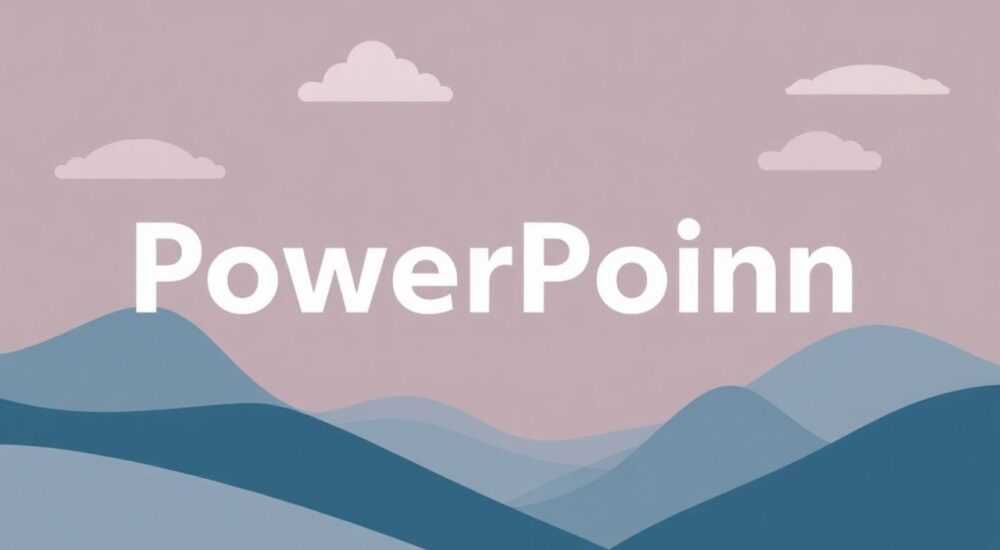
Как установить шрифт для презентации powerpoint
Установка шрифта для презентации в PowerPoint — это важный этап создания визуально целостного и профессионального выступления. Несмотря на кажущуюся простоту, процесс может вызывать трудности, особенно если шрифт не отображается на другом устройстве или требует установки из внешнего источника. Чтобы презентация корректно открылась у всех зрителей, нужно не только выбрать подходящий шрифт, но и правильно его интегрировать в файл.
Создание презентации — это не просто подбор текста и изображений, а продуманная типографика, где каждый элемент влияет на восприятие информации. Шрифт задаёт тон: деловой, креативный, строгий или дружелюбный. Однако даже самый идеальный выбор может «сломаться», если получатель не имеет установленного шрифта. В результате текст может отобразиться стандартным шрифтом, что испортит весь дизайн. Поэтому важно не только выбрать стиль начертания, но и обеспечить его стабильную работу на любом устройстве. В этой статье мы детально разберём, как установить шрифт для презентации PowerPoint, какие форматы поддерживаются, как встроить шрифты в файл и избежать распространённых ошибок.
Установка шрифта в систему
Прежде чем использовать шрифт в PowerPoint, его нужно установить в операционную систему. Без этого шага шрифт не появится в списке доступных в программе. Обычно шрифты распространяются в виде файлов с расширениями .ttf (TrueType Font) или .otf (OpenType Font). Эти форматы поддерживаются как Windows, так и macOS, но способы установки немного различаются.
На Windows 10 и 11 установка шрифта занимает всего несколько кликов. Скачанный файл шрифта можно открыть двойным щелчком, после чего откроется предварительный просмотр. В верхнем правом углу окна будет кнопка «Установить». Нажав её, вы добавите шрифт в систему. Альтернативный способ — перетащить файл шрифта в папку «Шрифты» (C:WindowsFonts), которая доступна через Проводник или Панель управления.
На macOS процесс аналогичен: достаточно открыть файл шрифта с помощью приложения «Просмотр шрифтов», затем нажать «Установить шрифт». Система автоматически добавит его в библиотеку. После установки перезапускать PowerPoint не требуется — новый шрифт появится в списке сразу после обновления программы.
Если вы работаете в команде или готовите презентацию для коллег, обязательно уточните, установлен ли нужный шрифт на их устройствах. В противном случае они увидят замену шрифта на системный, что может повлиять на макет. Особенно это критично для кастомных или дизайнерских шрифтов, которые не входят в стандартный набор Microsoft Office.
Пошаговая инструкция для Windows
- Скачайте файл шрифта (.ttf или .otf) с доверенного сайта, например Google Fonts, DaFont или FontSpace.
- Найдите скачанный файл в папке «Загрузки» и дважды щёлкните по нему.
- В открывшемся окне предварительного просмотра нажмите кнопку «Установить».
- Дождитесь завершения установки и откройте PowerPoint.
- Проверьте наличие шрифта в меню «Шрифт» на вкладке «Главная».
Добавление шрифта в PowerPoint
После установки шрифта в систему он автоматически становится доступным в PowerPoint. Откройте программу, создайте новую презентацию или откройте существующую. Выделите текстовое поле, которое нужно изменить, и перейдите на вкладку «Главная». В группе «Шрифт» найдите выпадающий список со всеми доступными шрифтами. Пролистайте вниз — там должен появиться ваш недавно установленный шрифт.
Если шрифт не отображается, попробуйте перезапустить PowerPoint. Иногда программа не обновляет список шрифтов без перезагрузки. Также убедитесь, что вы установили именно тот файл, который открывается — некоторые шрифтовые пакеты содержат несколько файлов (например, Regular, Bold, Italic), и каждый из них нужно устанавливать отдельно.
PowerPoint позволяет быстро применять шрифт ко всему слайду или всей презентации через функцию «Замена шрифта». Для этого:
- Перейдите на вкладку «Главная» → «Редактирование» → «Заменить» → «Заменить шрифты».
- В открывшемся окне выберите шрифт, который хотите заменить (например, Calibri).
- Во втором поле выберите новый шрифт из списка.
- Нажмите «Заменить» — все вхождения старого шрифта будут изменены.
Это удобно при массовом обновлении оформления, особенно если презентация уже содержит много текста. Однако будьте осторожны: замена применяется ко всем слайдам, включая заголовки и подзаголовки, если они используют выбранный шрифт.
Как использовать шрифт в мастере слайдов
Чтобы шрифт стал частью фирменного стиля презентации, его можно задать в мастере слайдов. Это гарантирует единообразие на всех слайдах.
- Перейдите на вкладку «Вид» → «Образец» → «Образец слайдов».
- Выберите главный образец (верхний слайд в левой панели).
- Выделите текстовые поля для заголовков и основного текста.
- Измените шрифт на нужный, задайте размер, цвет и интерлиньяж.
- Закройте режим образца — изменения применятся ко всем слайдам, основанным на этом макете.
Теперь любой новый слайд будет автоматически использовать установленный шрифт. Это особенно полезно при создании корпоративных презентаций, где важна единая визуальная идентичность.
Встраивание шрифтов в файл презентации
Один из самых важных шагов — встраивание шрифтов в файл. Даже если вы установили шрифт на своём компьютере, при открытии презентации на другом устройстве он может не отобразиться. PowerPoint по умолчанию не встраивает шрифты, чтобы уменьшить размер файла. Но эту настройку можно изменить.
Чтобы встроить шрифты:
- Откройте презентацию в PowerPoint.
- Перейдите в «Файл» → «Параметры» → «Сохранение».
- Найдите раздел «Встраивание шрифтов в файл».
- Поставьте галочку «Встроить шрифты в файл».
- Выберите один из двух вариантов: встроить все символы или только используемые.
Рекомендуется выбирать «Только символы, используемые в презентации» — это экономит место. Полное встраивание увеличивает размер файла, особенно если шрифт содержит множество символов (например, кириллицу, латиницу, иероглифы).
Тип встраивания |
Плюсы |
Минусы |
Все символы |
Полная доступность шрифта для редактирования |
Большой размер файла |
Только используемые символы |
Компактный размер, достаточный для просмотра |
Ограниченная возможность редактирования текста |
После включения этой опции сохраните презентацию в формате .pptx. Теперь она будет открываться корректно на любом компьютере, даже если нужный шрифт не установлен.
Совместимость и типичные ошибки
Несмотря на простоту процесса, пользователи часто сталкиваются с проблемами. Одна из самых частых — шрифт установлен, но не отображается в PowerPoint. Причины могут быть разными: повреждённый файл шрифта, конфликт имён, блокировка антивирусом или ограничения лицензии.
Некоторые шрифты имеют лицензионные ограничения, запрещающие их встраивание. В таком случае PowerPoint покажет предупреждение при попытке сохранить файл с встроенными шрифтами. Решение — использовать альтернативный шрифт с разрешённой лицензией или согласовать использование с правообладателем.
Другая ошибка — шрифт отображается на экране, но при печати или экспорте в PDF меняется. Это связано с тем, что система печати или конвертер PDF не может получить доступ к шрифту. Решение — всегда экспортировать презентацию в PDF с включённой опцией «Встраивать шрифты».
Чек-лист перед отправкой презентации
- Установлен ли шрифт на моём компьютере?
- Отображается ли он в PowerPoint?
- Включено ли встраивание шрифтов в настройках сохранения?
- Проверена ли презентация на другом устройстве без установленного шрифта?
- Экспортирован ли PDF с встроенными шрифтами?
Советы по выбору и использованию шрифтов
Выбор шрифта — это не только вопрос эстетики, но и читаемости. На крупных экранах плохо прорисованные шрифты теряют чёткость, а слишком декоративные — мешают восприятию. Эксперты рекомендуют придерживаться правила: один шрифт для заголовков, другой — для основного текста.
Беззасечные шрифты (sans-serif), такие как Arial, Helvetica, Roboto или Inter, лучше всего подходят для презентаций. Они читаются с большого расстояния и хорошо смотрятся на проекторах. Засечные шрифты (serif), например Times New Roman, больше подходят для печатных материалов.
Не используйте более двух шрифтов в одной презентации. Исключение — случаи, когда вы намеренно создаёте контраст (например, креативный заголовок и нейтральный текст). Размер шрифта также важен: минимум 24 pt для основного текста, 36–44 pt для заголовков.
Популярные бесплатные шрифты для PowerPoint
- Roboto — современный, универсальный, отлично читается на экране.
- Open Sans — открытый шрифт от Google, мягкие формы, высокая читаемость.
- Montserrat — геометричный, стильный, популярен в корпоративных презентациях.
- Lato — дружелюбный, округлый, подходит для образовательных и стартап-презентаций.
- PT Sans — российский шрифт с отличной кириллицей, поддерживается Microsoft.
«Сегодня многие забывают о типографике, считая её второстепенной. Но шрифт — это голос вашей презентации. Он может усиливать сообщение или, наоборот, его искажать. Я всегда начинаю с выбора шрифта, ещё до написания первого слайда. И обязательно встраиваю его в файл. За последние пять лет ни одна из моих презентаций не «сломалась» на чужом компьютере — и это благодаря вниманию к деталям.»
Установка шрифта в PowerPoint — это многоэтапный процесс, включающий загрузку, установку в систему, применение в программе и встраивание в файл. Каждый шаг важен для того, чтобы презентация выглядела одинаково на любом устройстве. Современные инструменты позволяют легко работать с кастомными шрифтами, но требуют внимания к совместимости и лицензированию.
- Установите шрифт в систему через Панель управления или папку Fonts.
- Проверьте его наличие в PowerPoint после перезапуска программы.
- Используйте режим «Образец слайдов» для применения шрифта ко всей презентации.
- Включите опцию «Встроить шрифты в файл» при сохранении.
- Проверяйте презентацию на устройстве без установленного шрифта.